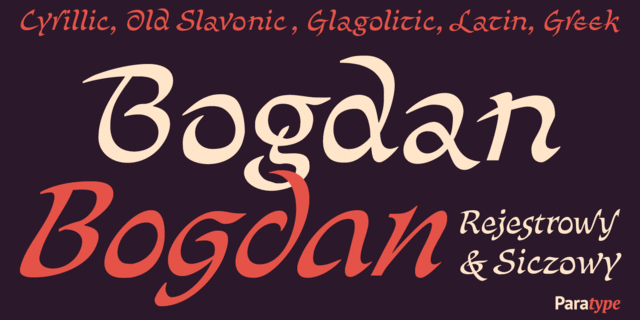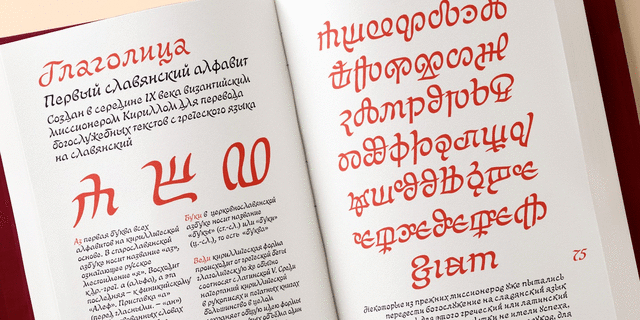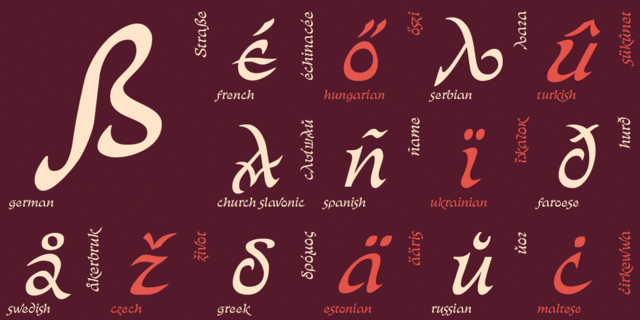
Оригинальный рукописный шрифт разработан Виктором Хариком на основе украинской скорописи XVI-XVII веков, в частности универсалов Богдана Хмельницкого, отсюда название. Лицензирован компанией ПараТайп в 2006 году. Имитирует письмо ширококонечным птичьим пером с нажимом, что придаёт ему неформальную живость. В комплекте разработаны знаки кириллицы, глаголицы, латиницы и греческого алфавита, включая знаки старославянской кириллицы, в двух вариантах: Реестровом (регулярном) и Сичовом (альтернативном). Предназначен для акциденции, но вполне пригоден для небольших текстов. Прекрасно подходит для историко-культурных тем, связанных с Европой XV-XVII веков.
Ассоциации c начертанием Bogdan SiczowyКачества и характер:
лихой, развязный, воинственный, смелый, храбрый, динамичный, вьющийся, изогнутый, волнистый, эмоциональный, замысловатый, оригинальный, свободный, пластичный, сильный, самобытный, резкий, мятежный, этничный, природный, натуральный, традиционный, старинный, казацкий, вольный, гордый, пьяный, народный, степной, конный, животный, анималистический, остроумный, веселый, шутливый, колоритный, живой, темпераментный, активный, органический, племенной